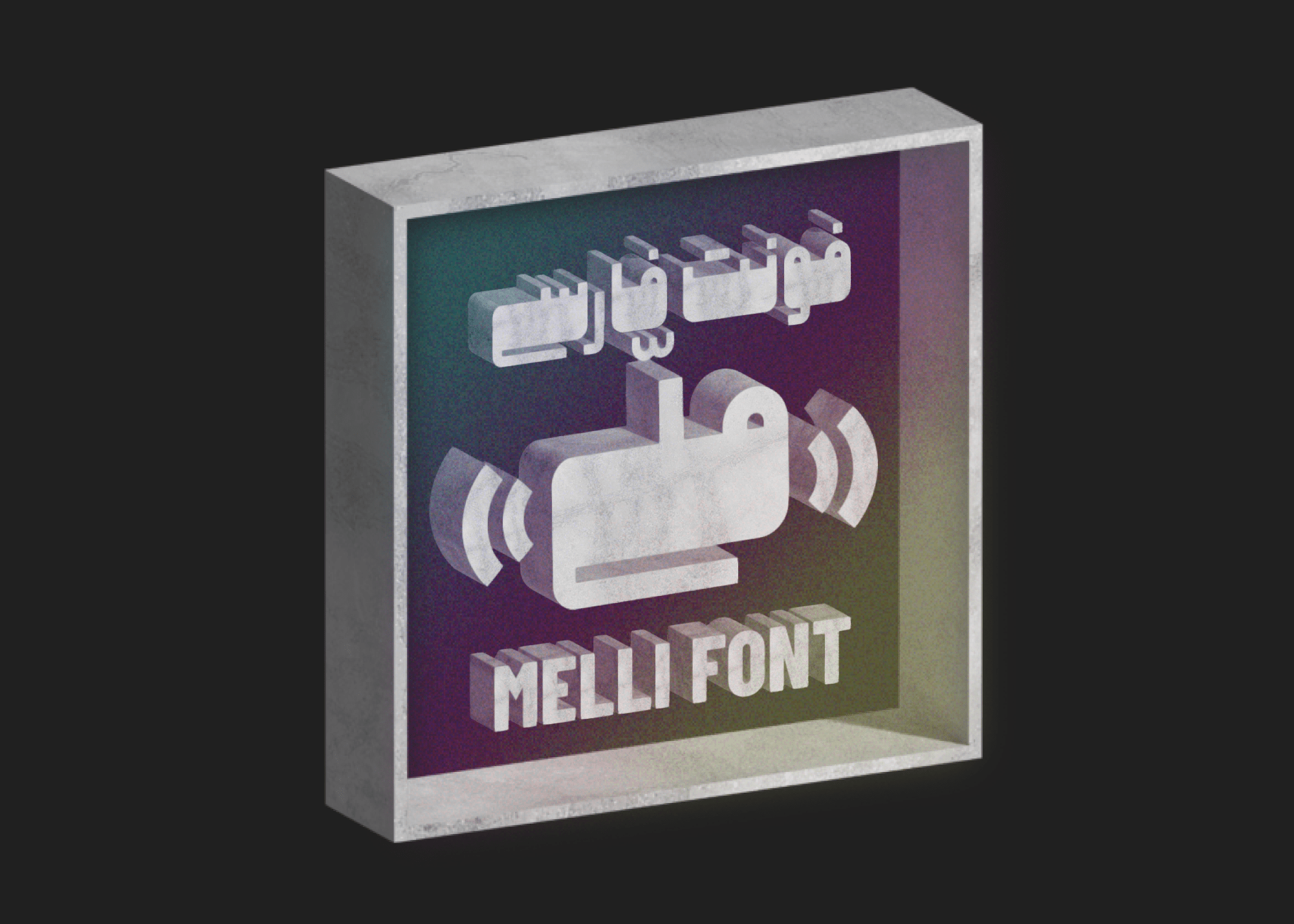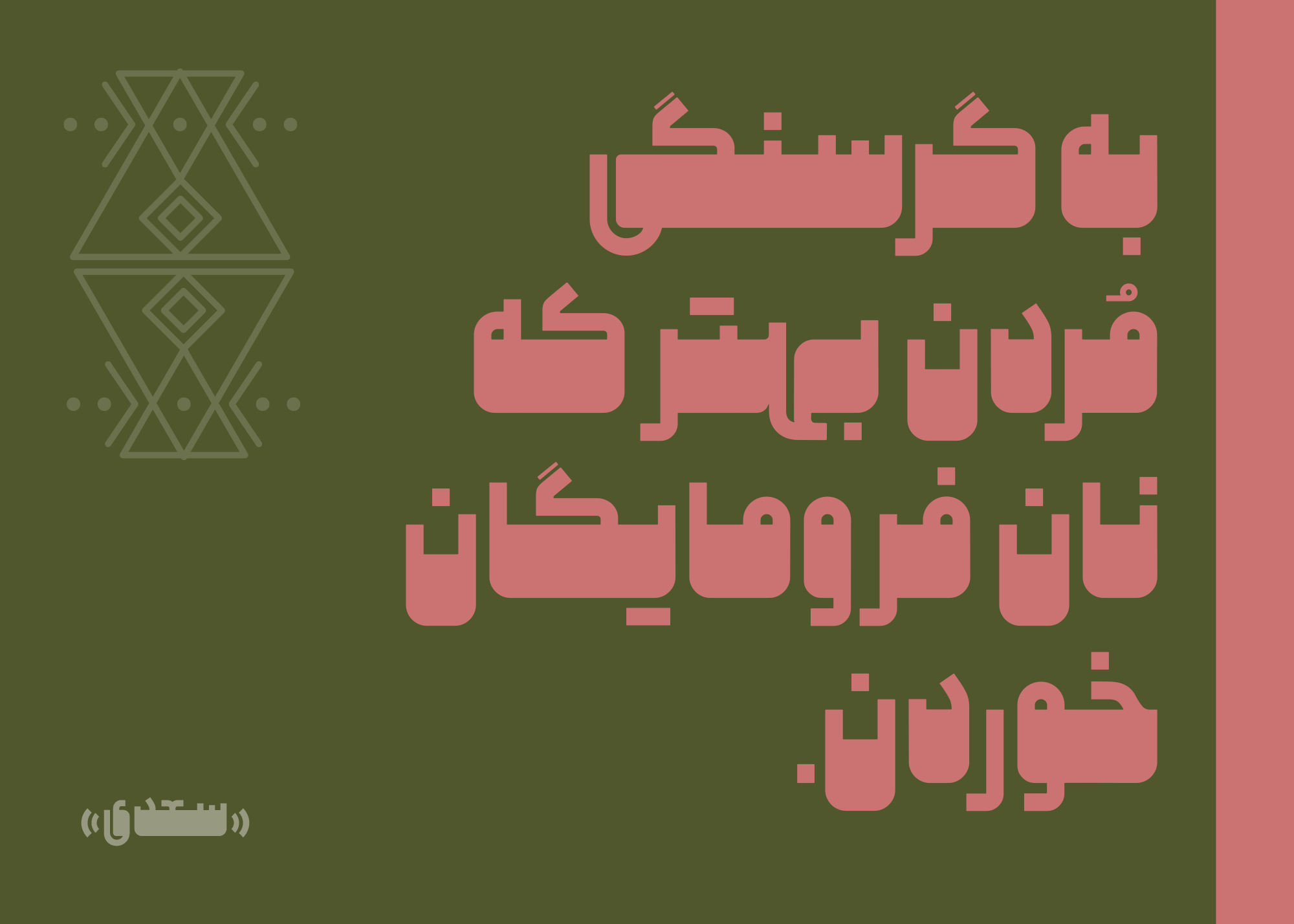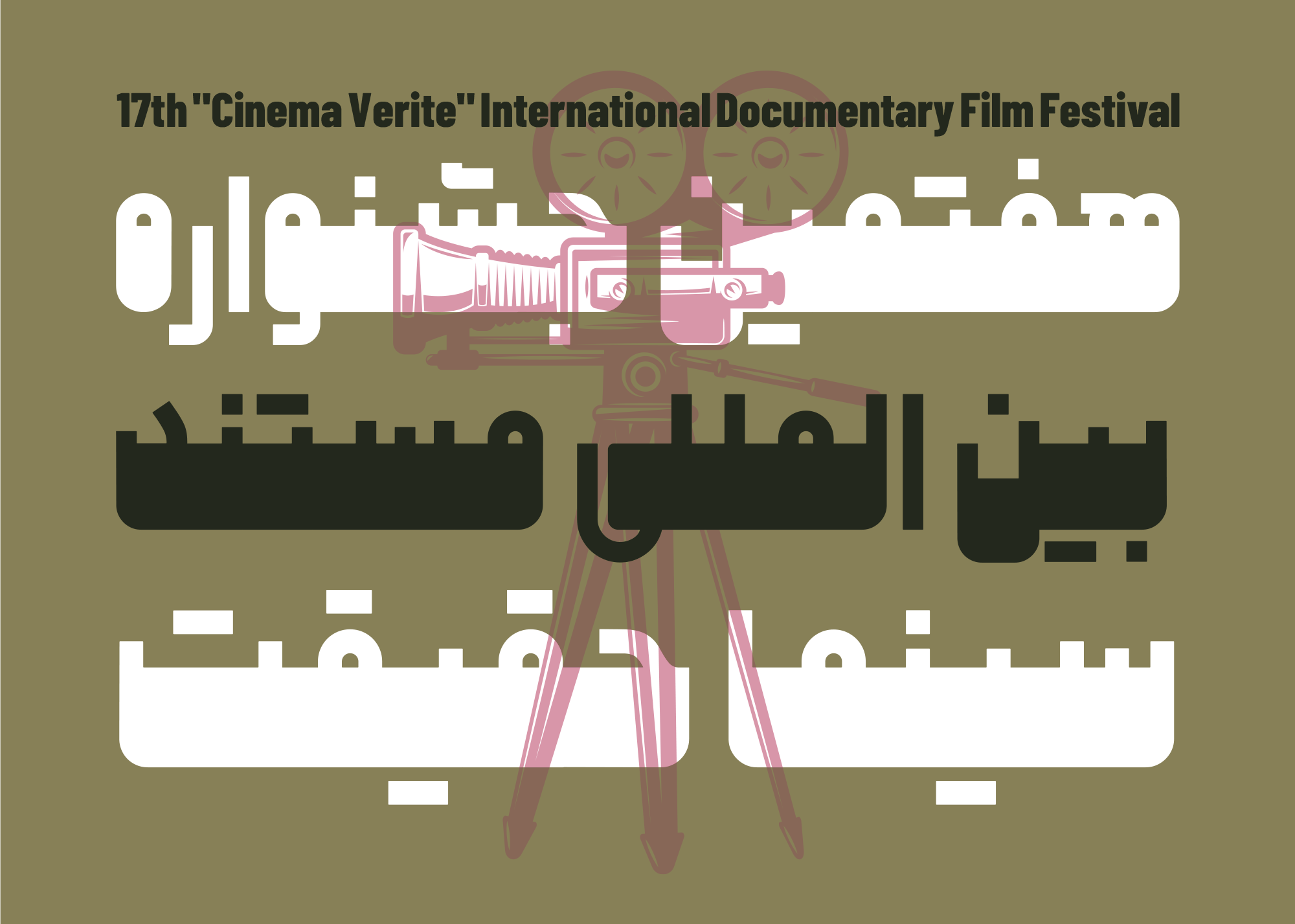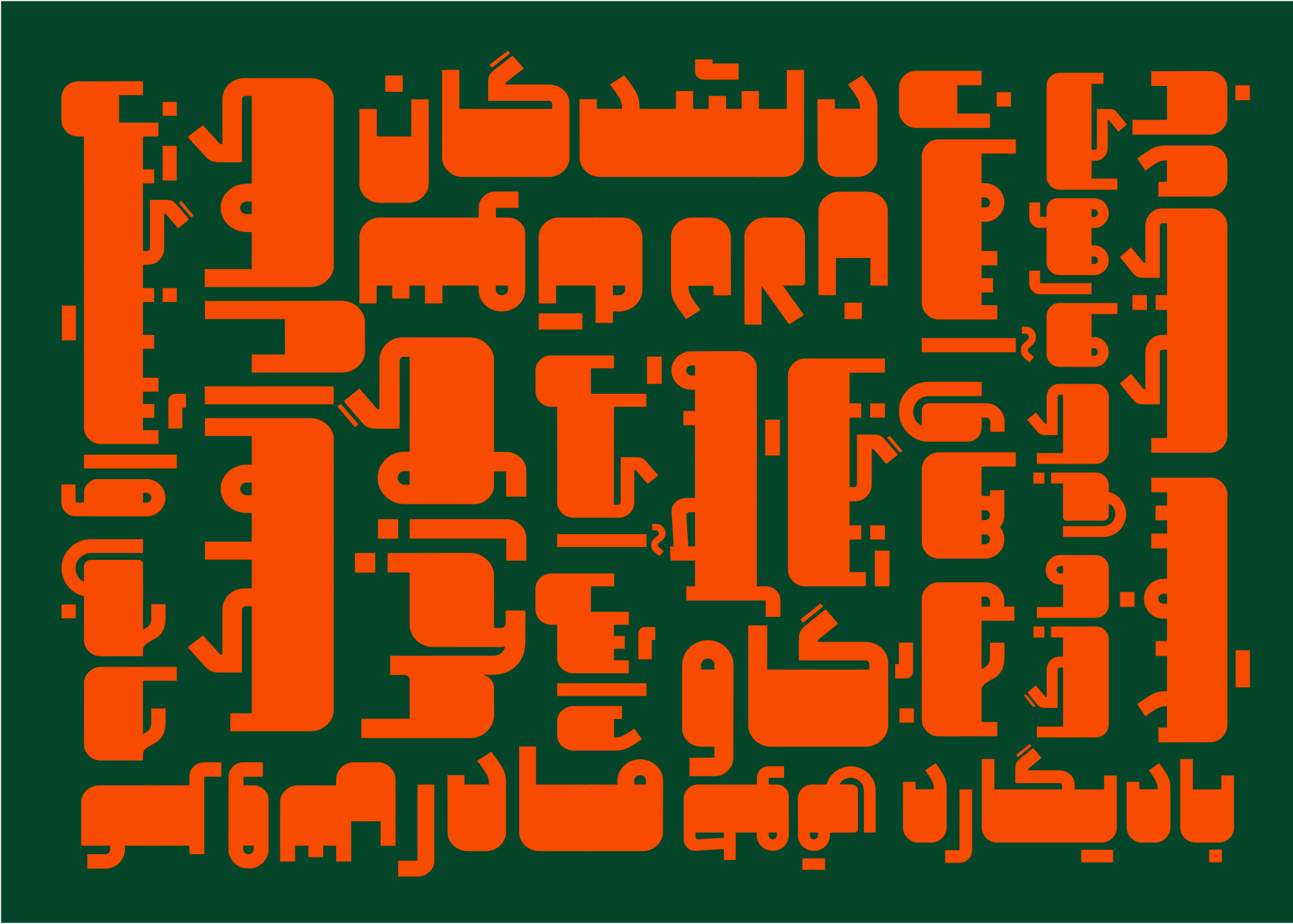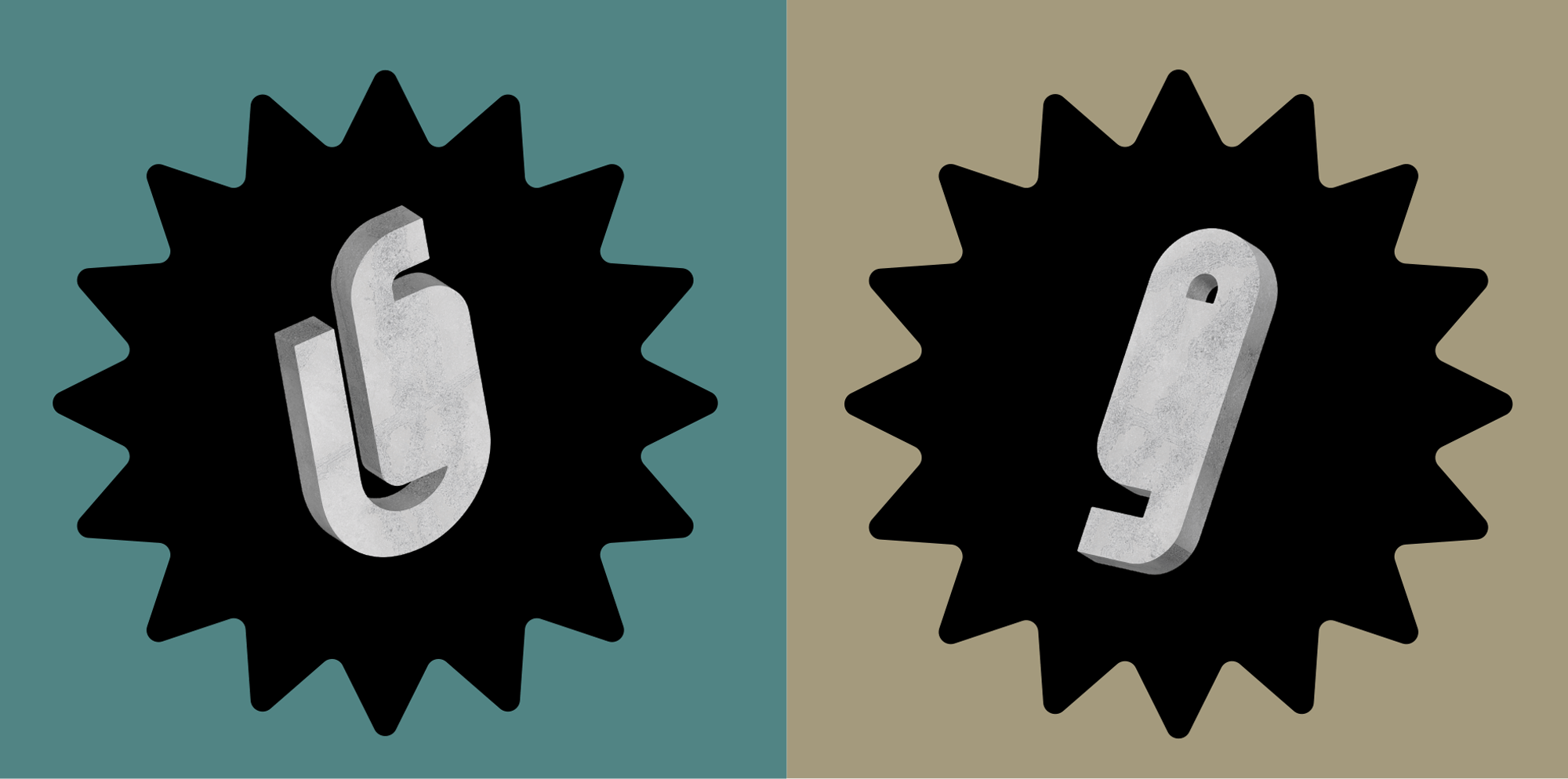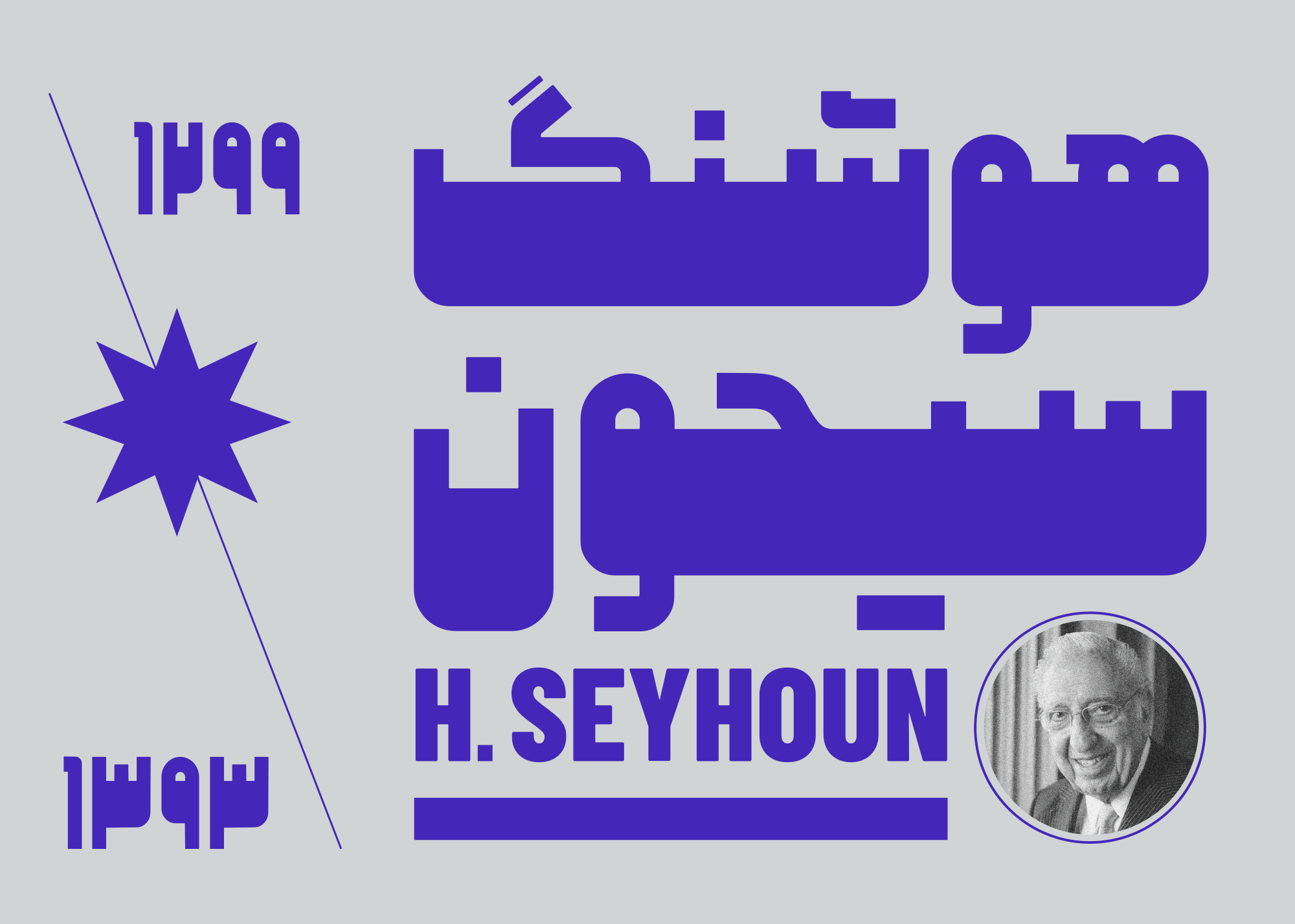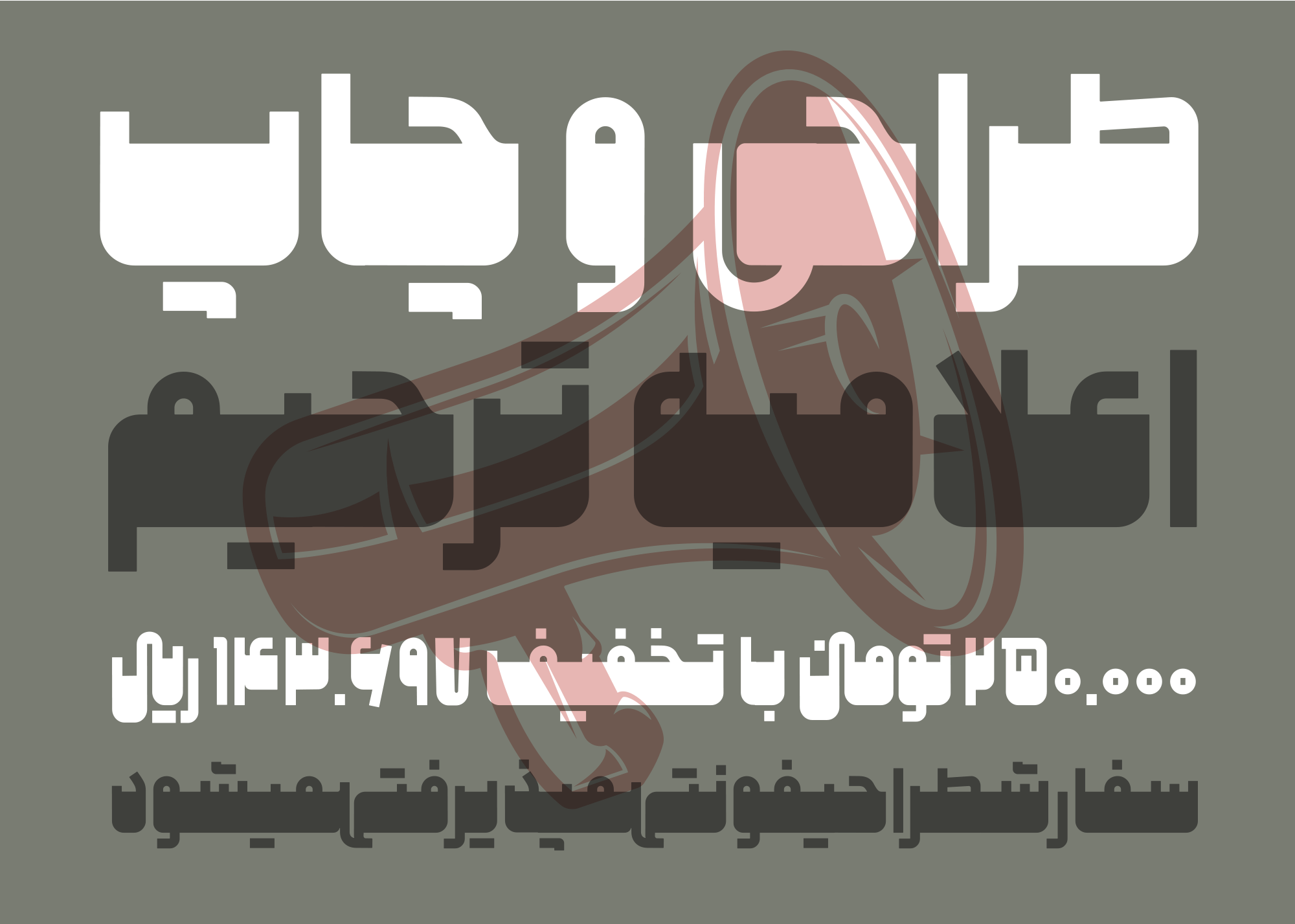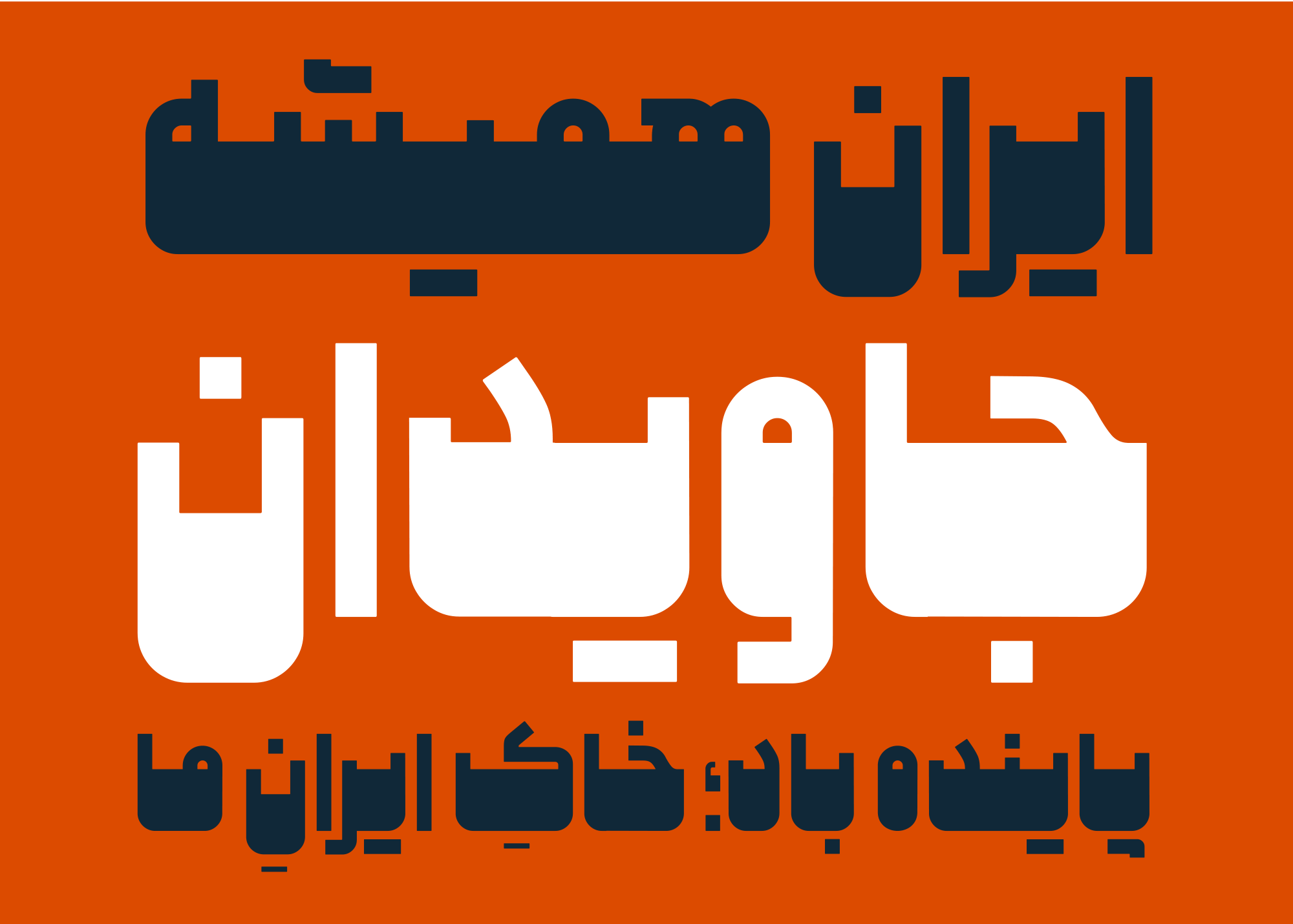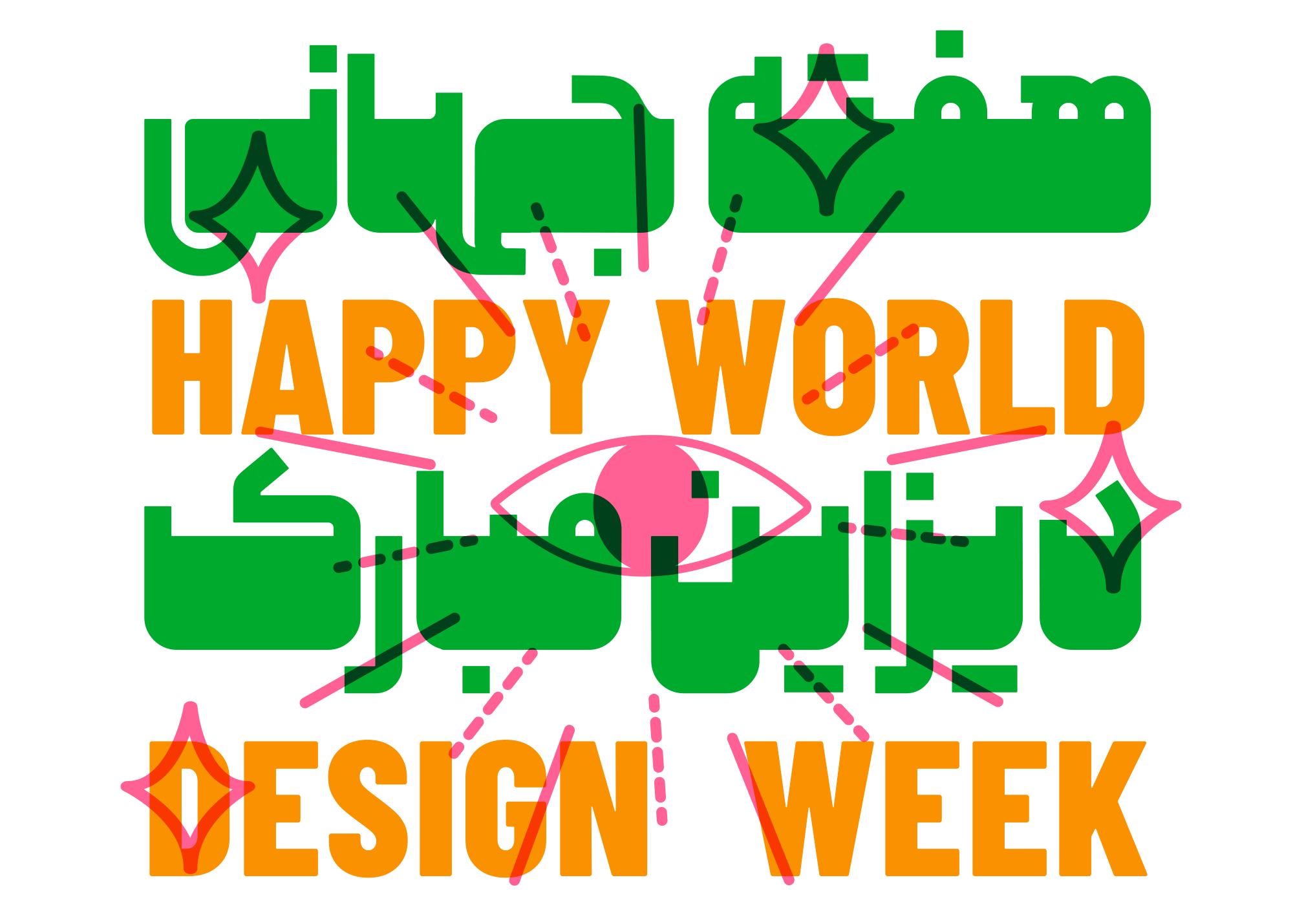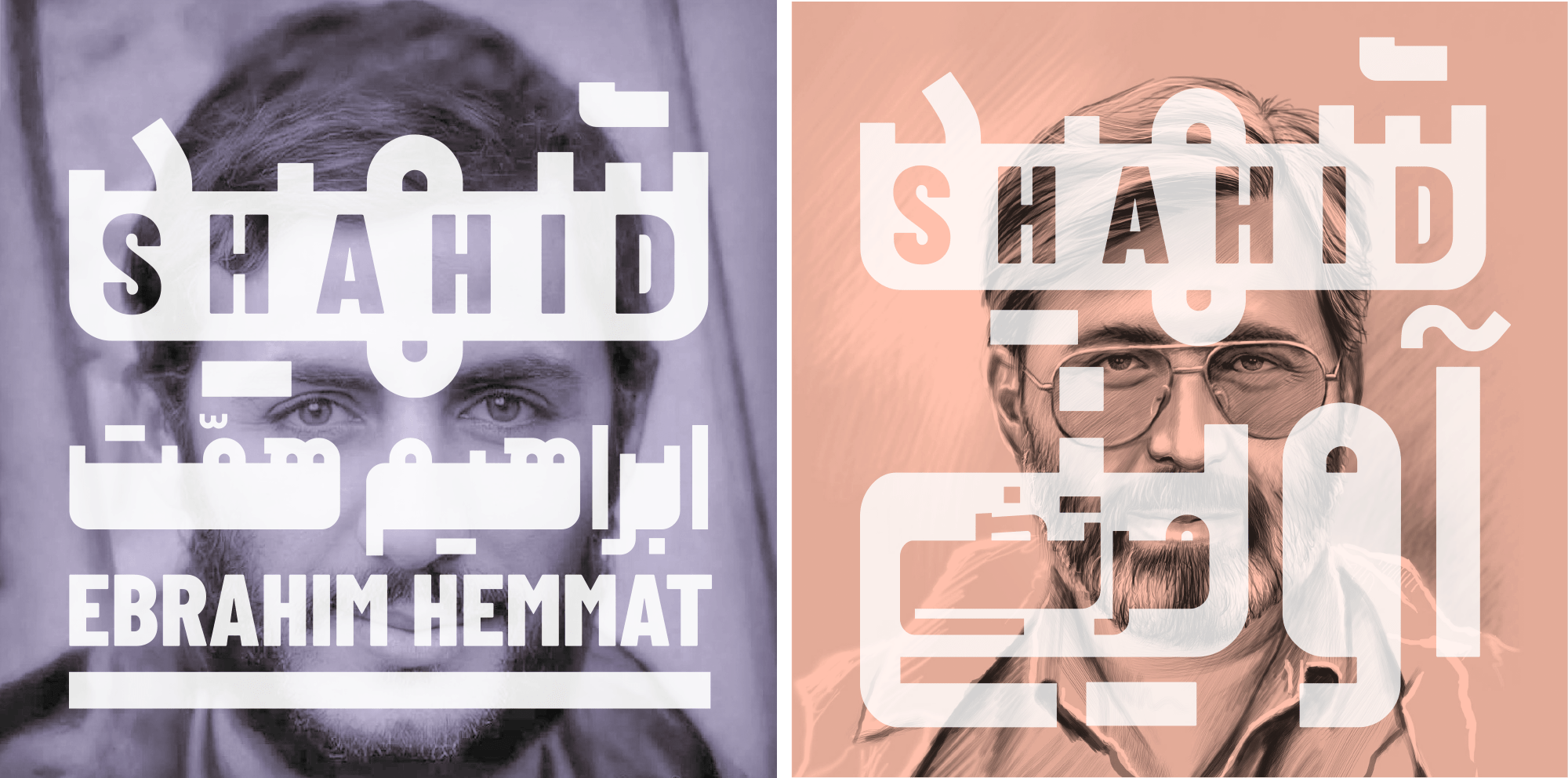
تایپوگرافی با فونت ملی بسیار آسان است. حروف باکسهای فشرده و منظمی را تشکیل میدهند که به آسانی همنشین تصویر و قاب شما میشود.
فونت ملی برای موضوعات حماسی، ملی، نوستالژی بهترین انتخاب است اما به دلیل سادگی و مینیمال بودن میتواند برای انواع موضوعات مدرن و امروزی نیز مناسب باشد.
حروف جایگزین
در فونت ملی میتوانید حروف ک و گ را به حالت کشیده تغییر دهید و مقدار کشیدگی را ۲ درجه افزایش دهید.
حروف ه وسط و آخر ( ﮧ ﮩ مدل نستعلیق) دارای حالتهای جایگزین هستند.
حرف ی میتواند بصورت معکوس ( ے ) تغییر یابد و میزان کشیدگی ۲ درجه قابل افزایش است.
حروف س ش میتواند به حالت کشیده تغییر کند.
کاسه حروف در (ن س ش ص ض ق ل) میتواند به حالت گرد تغییر یابد.
نسخه فشرده شده ریال و تومان
گلیفهای اختصاصی برای ریال و تومان برای نمایش بصورت فشرده تر در فونت موجود است.
همچنین امکان فارسی کردن / همتراز کردن و تغییر تراز عمودی اعداد وجود دارد.